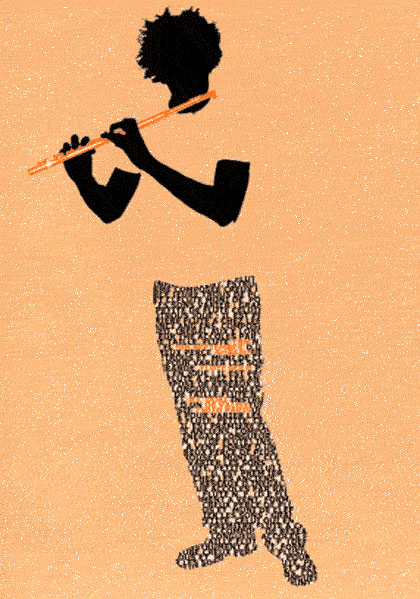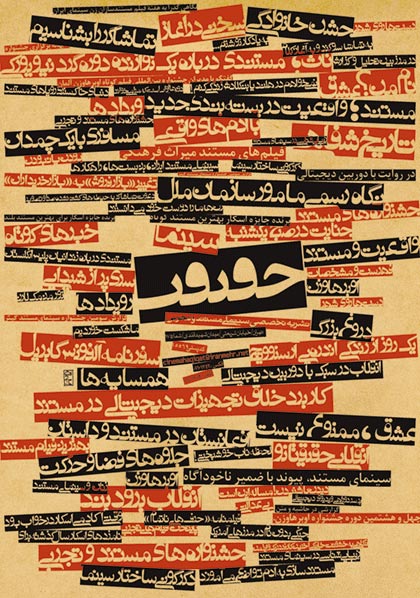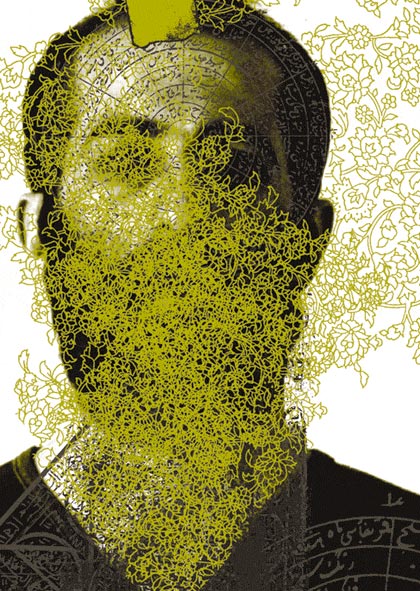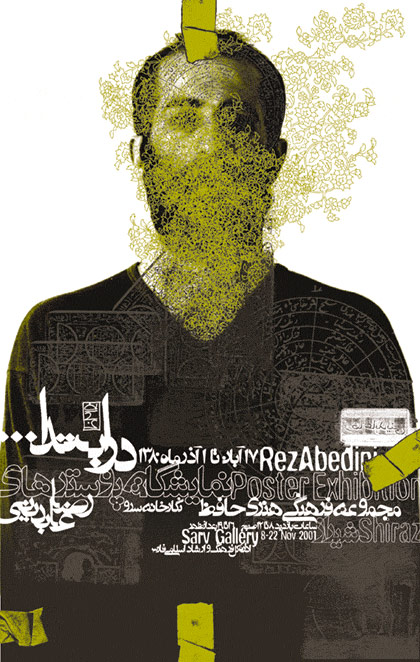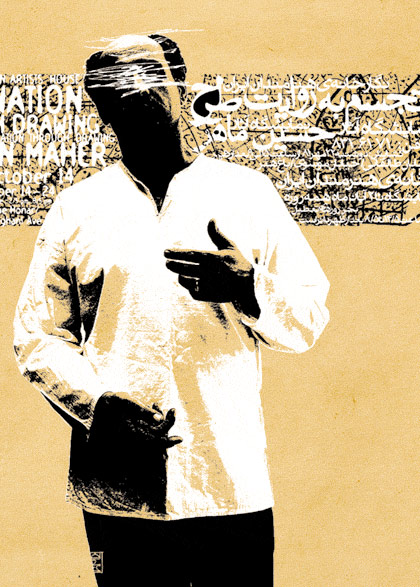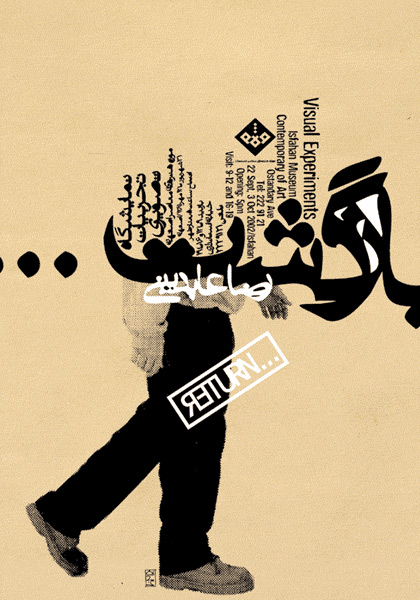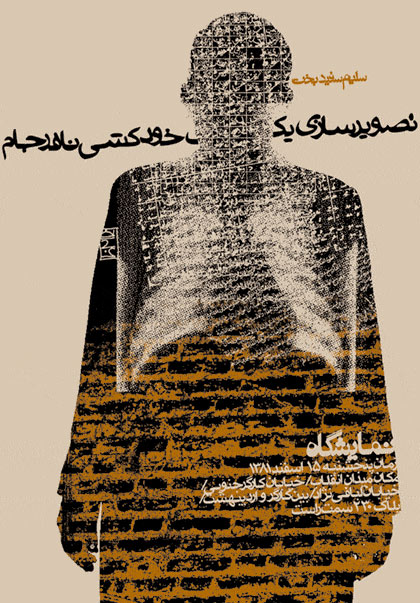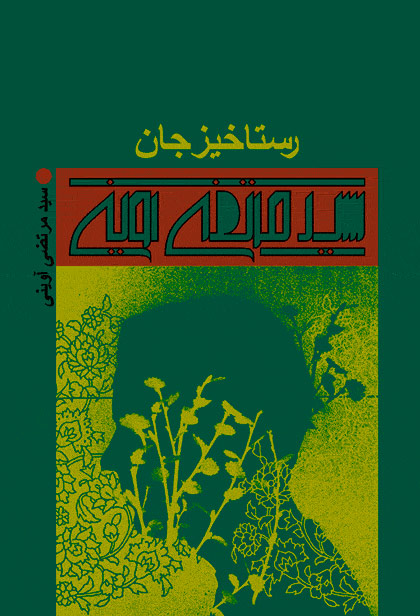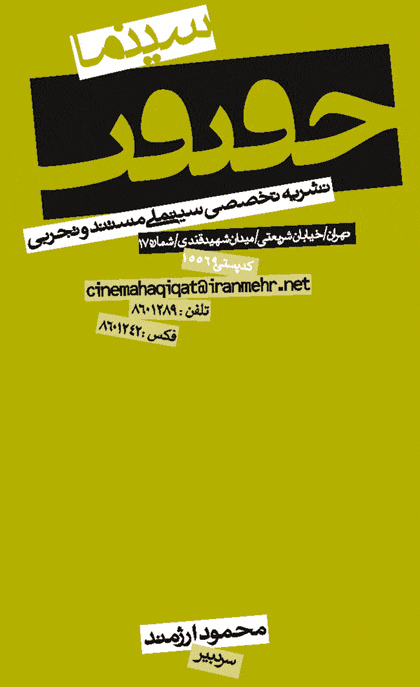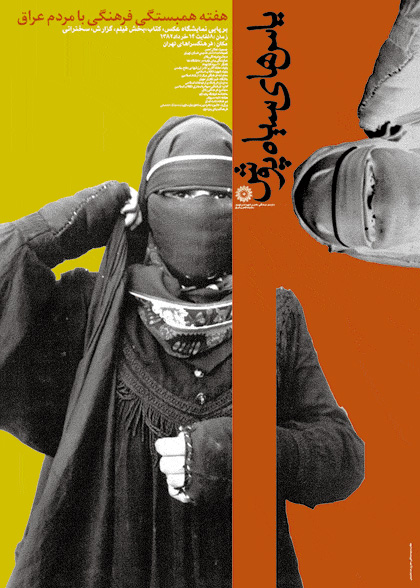
Dire que c’était une découverte, non, je connaissais déjà l’œuvre de Reza Abedini par les différentes publications que nous pouvions approcher par les librairies spécialisées ou tout simplement par son site personnel. Mais de voir de près ses affiches exposées dans un lieu magique, sorte d’ancien gymnase qui n’est pas sans rappeler celui d’Albert Hollenstein (le Gymnasium), poutres et murs blancs immaculés, reste un choc visuel majeur. C’est en allant à la conférence d’Annie Vernay-Nouri dont je vous ai parlé précédemment qu’entouré de l’œuvre de Reza nous écoutions l’histoire de l’écriture arabe qui nous a révélé entre autres le décalage entre l’orient et l’occident concernant l’invention de la lettre mobile en plomb. C’est seulement au milieu XIXe siècle, et encore sous l’influence d’imprimeurs européens, que le monde arabe commença à pratiquer l’industrie du livre.
Pour revenir à Reza Abedini, vous trouverez comme d’habitude sa bio sur Wikipedia de même que directement sur son site (avec de nombreux autres affiches et réalisations qui ne figurent pas ci-dessous). Je vous fais un copier-collé au bas de cette note, juste pour garder l’unité de cette publication. Suis dans l’incapacité de rajouter ou de retirer ou même de réécrire une bio que je connais à peine. D’ailleurs ce n’est pas pour faire assaut de connaissance que je publie cette note, au contraire. C’est plutôt une affaire épidermique. Une sensation de me sentir à l’aise, chez moi au milieu de cet œuvre à la fois si loin et si près de nos sensibilités.
Loin, sans doute si l’on songe à la calligraphie arabe auquel je ne comprends rien, sinon l’aspect purement décoratif. Mais c’est précisément là que Reza Abedini nous amène. Une connaissance historique de l’écriture arabe, une pratique d’abord traditionnelle puis, tel un rebelle qu’il n’est pas, Reza en vient à raprocher les deux cultures occident-orient. On ne peut pas s’empêcher de songer à tous les apports graphiques allant du DaDa au constructivisme russe en passant par l’humour et les symboliques Lubaliniens. Un graphic-designer aussi Alvin Lustig, qui opéra dans les années 40-50… son œuvre que nous avons évoqué ici, a du forcément influencer Reza. Il ne s’agit à aucun moment de plagiat, ni de revival, ni même d’inspiration directe. Plutôt d’une porosité aux cultures occidentales, un désir de rapprocher les deux formes de sensibilités.
En regardant les affiches d’Abedini, j’ai toujours un doute. Je ne sais pas s’il veut «tirer» la culture de son pays d’origine (l’Iran) vers nos sensibilités occidentales, ou bien au contraire s’il veut nous amener nous autres «infidèles» à découvrir la culture calligraphique de ses origines. Sans doute il y a des deux. Sans doute que c’est dans l’entre-eux des sensibilités extrêmes qu’il trouve l’énergie de s’exprimer pour toucher l’âme du plus grand nombre. Parce que malgré toutes les recherches abstraites et conceptuelles son œuvre reste abordable et universelle. C’est certainement là, le signe des grands artistes.
Juste peut-être de rajouter une remarque faite par Annie Vernay-Nouri lors de son exposé: l’utilisation des couleurs… sépia, marron, terre de sienne, des couleurs chaudes et parfois contrastées avec des orange ou vert, restent dans la plus grande tradition décorative persane et islamique. (voir sa bio en anglais sous les photos).